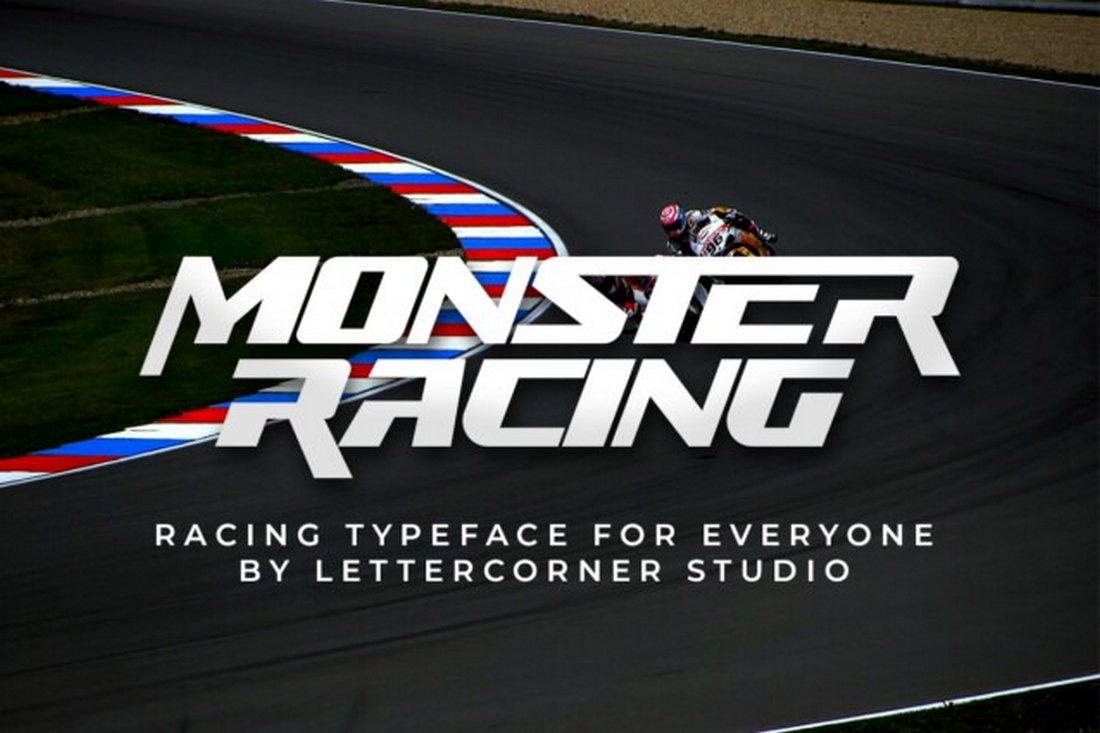
25+ Best Racing Fonts (Racing Number, Script Fonts & More)
25+ Best Autorennsport Fonts (Racing Number, Script Fonts & More)
25+ Beste Rennschriftarten (Rennnummer, Skriptschriftarten & mehr)
Heute präsentieren wir Ihnen eine Sammlung der besten Rennschriftarten, um Ihren Designs das Gefühl von Action und Bewegung zu verleihen.
Für diese Sammlung haben wir verschiedene Stile von Rennthemen-Schriftarten ausgewählt. Von Retro-Stilen, die von der glitzernden Welt des Vintage-Motorsports inspiriert sind, bis hin zu modernen futuristischen Schriftarten, die die elegante Raffinesse der heutigen Automobilindustrie verkörpern, haben wir Schriftarten für alle Ihre Bedürfnisse.
Ob Sie eine coole Rennschrift benötigen, um ein Verpackungsdesign für einen Kunden zu gestalten, ein Logo für eine Automarke oder sogar an einem persönlichen Projekt arbeiten, diese Schriftarten werden Ihr Projekt sicher mit voller Geschwindigkeit vorantreiben.
Race Freak - Rennthemen-Schriftart
Dies ist eine dynamische, auf Rennen ausgerichtete Schriftart, die sorgfältig für den Einsatz in Gaming- und Automobilprojekten entwickelt wurde. Diese Schriftart eignet sich perfekt für die Erstellung selbstbewusster Überschriften, einzigartiger Logos und kühner Markenidentitäten. Sie bietet grundlegende lateinische Buchstaben A-Z, Zahlen und Symbole sowie Unterstützung für mehrere Sprachen.
Throttle - Moderne Rennsport-Schriftart
Throttle ist eine zeitgenössische und dynamische Rennsport-Schriftart, die das Gefühl von Geschwindigkeit verkörpert. Mit ihren geschmeidigen Linien und ihrem starken Design eignet sie sich hervorragend für den Einsatz in Rennspielen, Sportveranstaltungen und Autobeschriftungen. Erhältlich in OTF-, TTF- und WOFF-Formaten enthält sie grundlegende lateinische Zeichen, Zahlen und Interpunktionen.
Pro Racing - Sportliche Schriftart
Schauen Sie sich Pro Racing an, eine sportliche Schriftart, die die Dynamik moderner Automobiltechnologie mit einem zukunftsweisenden Rennblick makellos verbindet. Mit vier Stilen und mehrsprachiger Unterstützung ist diese futuristische, elegante Schriftart perfekt für Projekte, die einen High-Tech-Look benötigen, von Automobilmarken bis hin zu Rennveranstaltungen.
Escalated - Schnelle Motorsport-Rennschriftart
Eine äußerst vielseitige, fette und solide Display-Schriftart. Sie ist perfekt für Projekte mit einem Renn- oder Sportthema geeignet, passt aber auch gut zu Branding, Gaming, Musik, Filmtiteln, Technologie und sogar zu weltraumorientierten Designs. Ihr Paket umfasst OTF-, TTF-, WOFF- und Ligaturformate.
Drag Racing - Sport-Display-Schriftart
Dies ist eine athletische, elegante Schriftart, die ideal für den Einsatz in Gaming-, Renn- und Automobilprojekten geeignet ist. Mit Großbuchstaben, Kleinbuchstaben, Symbolen, Interpunktionen, Zahlen und mehr ist diese vielseitige Schriftart hervorragend geeignet, um auffällige Überschriften, Logos, Brandings und Poster zu erstellen.
Two Race - Moderne Rennschriftart
Two Race ist eine moderne, von Rennen inspirierte Schriftart mit einem Satz fettgedruckter, sportlicher Zeichen. Perfekt für das Gestalten von Logos, Rennveranstaltungstiteln und Autostickern verleiht diese vielseitige Schriftart Ihren Projekten eine aufregende Geschwindigkeitsnote. Sie enthält zwei Stile und unterstützt alle Alternativen und Glyphen über Unicode (PUA) sowie OpenType-Funktionen.
FAST TRACK - Rennthemen-Schriftart
FAST TRACK ist eine Rennthemen-Schriftart, die Geschwindigkeit verkörpert und den aufregenden Geist des Rennens in Ihre Designs bringt. Ihre scharfen Ecken und ihre solide Form mit Aussparungen machen sie ideal, um Aufmerksamkeit zu erregen. Diese Schriftart eignet sich perfekt für den Einsatz in Renn-thematisierten Online-Spielen, Postern, Magazin-Covern, YouTube-Vorschaubildern und mehr.
Piston Race - Stilvolle Rennschriftart
Piston Race ist eine lebendige, sportliche Rennschriftart. Inspiriert von der aufregenden Welt des Rennsports, injiziert die robuste und dynamische Piston Race-Schriftart Ihren sportlichen Renn-Themendesigns ein Gefühl von Geschwindigkeit. Sie eignet sich besonders gut für Logos, Autosticker und Rennveranstaltungstitel.
DROPEX - Sport-Rennschriftart
DROPEX ist eine robuste und markante Typografie, die leicht Aufmerksamkeit erregt. Mit viel Sorgfalt erstellt, bietet sie eine entscheidende Einzigartigkeit, um Ihre Arbeit hervorzuheben. Sie umfasst OTF-, TTF- und WOFF-Formate sowie vier Stilvariationen. Mit Unterstützung für OpenType-Funktionen, Glyphen-Panels und mehrsprachige Zeichen.
MAXDRIVE - Renn- & Sport-Schriftart
MAXDRIVE ist eine weitere moderne Renn- und Sportthemen-Schriftart. Sie verkörpert das Gefühl von Geschwindigkeit und adrenalingeladener Renn-Action. Ihr Design zeichnet sich durch scharfe Ecken, fette Großbuchstaben und eine Linienart-Version für Kleinbuchstaben aus, die zusammen die dynamische Energie des Rennens betonen. Ideal für Renn-thematisierte Online-Spiele, YouTube-Vorschaubilder, Social-Media-Cover und mehr.